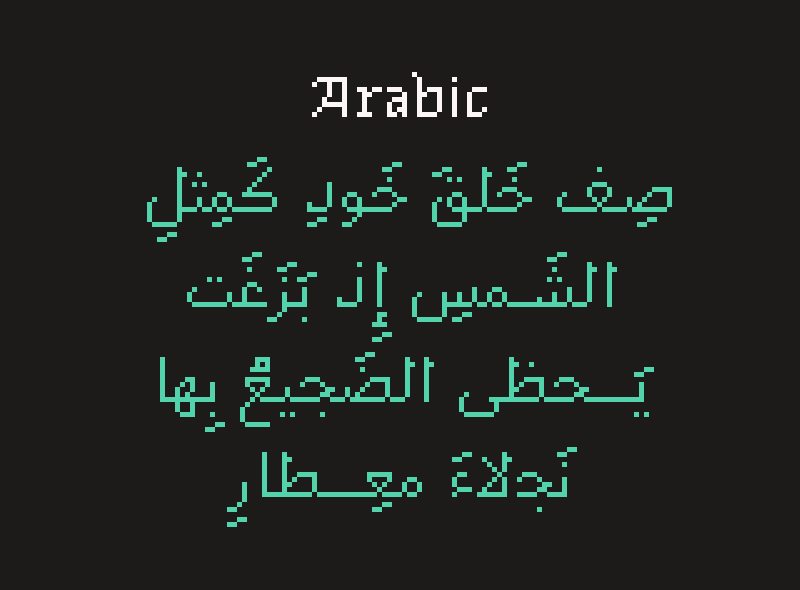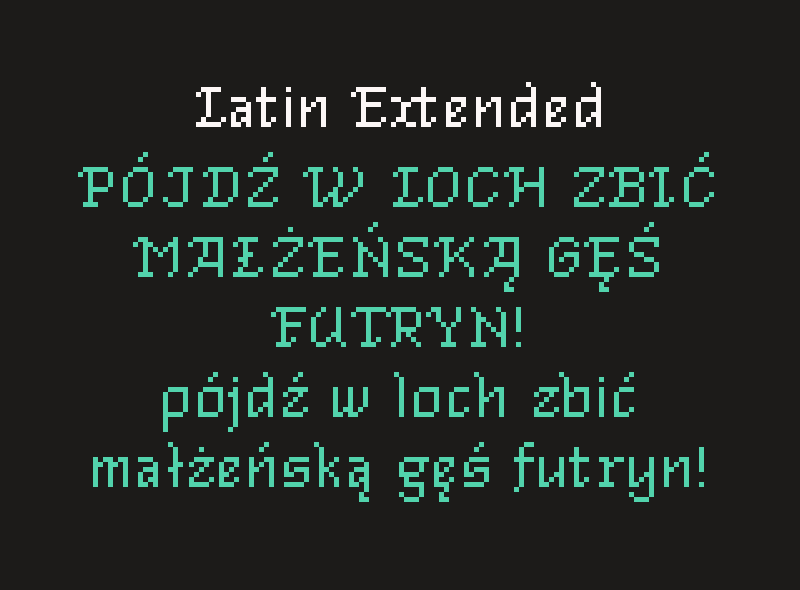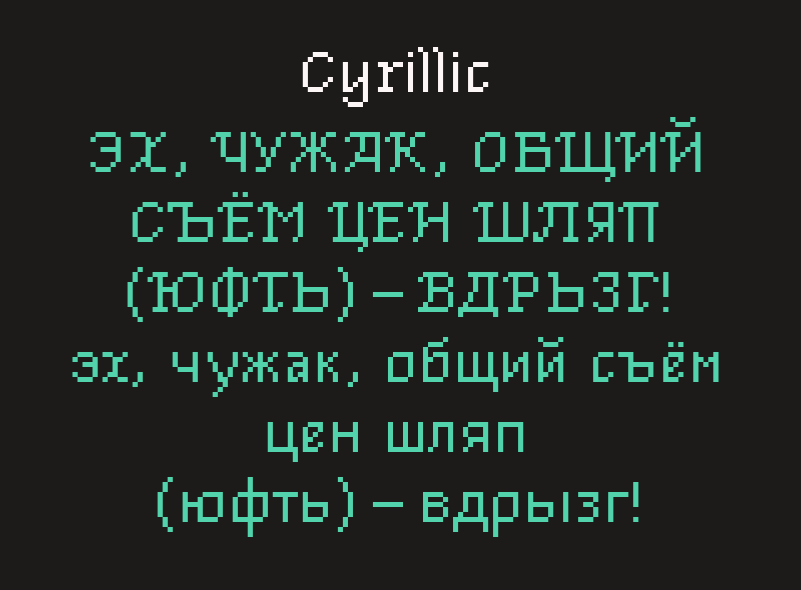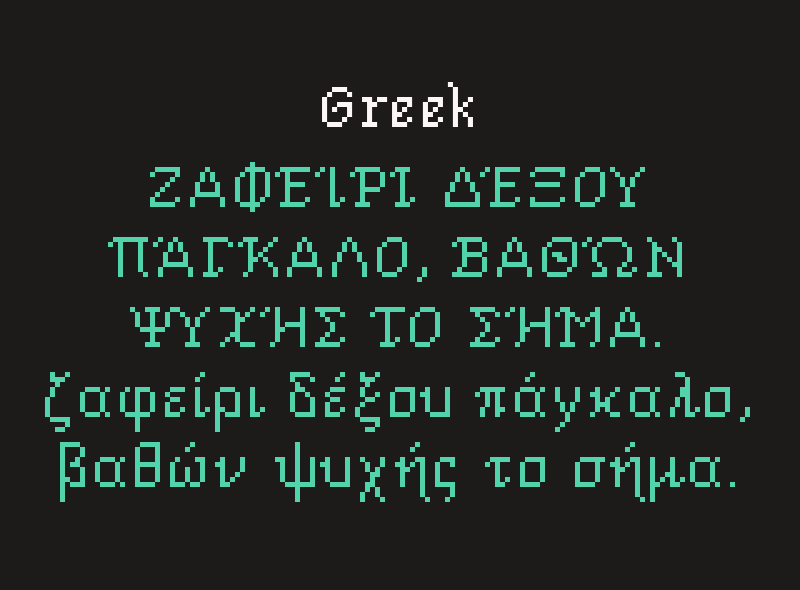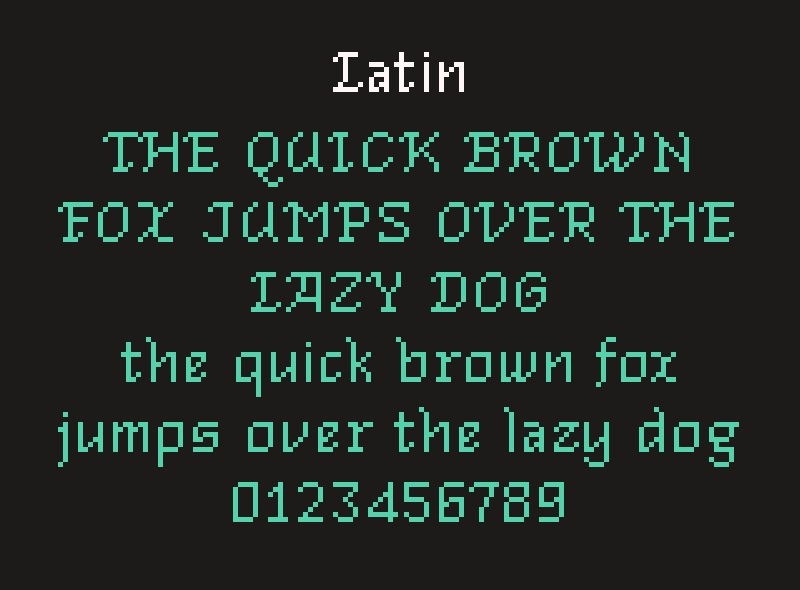
支持广泛本地化的像素PixelGlobal字体素材,专为需要广泛本地化支持的游戏而设计。
为了致力于让游戏本地化更加便捷,PixelGlobal 包含了 700 多个字形,涵盖拉丁文、西里尔文、希腊文和阿拉伯文,帮助您的游戏无需切换字体即可触达世界各地的玩家。
Windows-1252 字符集 ✓
Mac OS Roman ✓
拉丁语扩展 – A ✓
基本西里尔字母 ✓
单调希腊语 ✓
阿拉伯语(带音节符号) ✓
PixelGlobal 包含 700 多个字形,支持以下语言:
南非荷兰语 阿拉伯语 白俄罗斯语 克罗地亚语
捷克语 丹麦语 荷兰语 达里语
英语 法语 德语 希腊语
冰岛语、印尼语、意大利语、尼日利亚皮钦语
挪威语、波斯语、波兰语、葡萄牙语
俄语 西班牙语 斯瓦希里语 瑞典语
他加禄语 土耳其语 沃洛夫语
支持广泛本地化的像素PixelGlobal字体素材